18 cele mai bune fonturi de fotbal din 2023 (gratuit și premium)
Publicat: 2023-08-22V-ați chinuit vreodată să găsiți fontul perfect pentru a vă ridica proiectele de design cu tematică de fotbal? Nu mai căuta! În această postare pe blog, am compilat o listă cu cele mai bune 18 fonturi de fotbal care vă vor duce designul la următorul nivel.
Indiferent dacă creați un poster sportiv, un logo al unei echipe sau chiar o marfă pentru fani, aceste fonturi vor adăuga acel plus de autenticitate și entuziasm.
Acum, s-ar putea să vă întrebați, de ce sunt fonturile atât de importante în modelele de fotbal? Ei bine, fontul potrivit poate surprinde esența jocului, poate aprinde pasiunea și poate transmite energia și spiritul sportului.
Și odată cu creșterea popularității fotbalului la nivel mondial, este esențial să alegeți un font care să rezoneze cu publicul dvs.
În acest articol, vom explora diverse fonturi de fotbal care nu sunt doar atractive din punct de vedere vizual, ci și extrem de versatile. Aceste fonturi au fost atent selectate pe baza unicității, lizibilității și capacității lor de a completa design-urile legate de fotbal.
Vă vom oferi câteva statistici și date interesante despre fiecare font, permițându-vă să luați o decizie informată atunci când îl alegeți pe cel care se potrivește cel mai bine proiectului dvs. Așadar, pregătește-te să-ți îmbunătățești modelele de fotbal cu aceste fonturi incredibile!
Cele mai bune fonturi de fotbal premium
Sunteți un designer grafic și doriți să vă duceți proiectele la următorul nivel cu niște fonturi uimitoare de fotbal? Nu mai căuta! În această secțiune, am ales cu atenție cele mai bune fonturi premium de fotbal care vă vor îmbunătăți cu siguranță design-urile.
Nu ratați ocazia de a explora aceste opțiuni incredibile și de a vă duce proiectele la noi culmi.
Fotbal
Fotbalul este un font fantastic care este conceput special pentru siglele sportive moderne. Indiferent dacă lucrați la un logo de echipă sau la un proiect de design cu temă sportivă, acest font este garantat să vă scoată în evidență tipografia.
Acest font este perfect pentru a crea titluri atrăgătoare și care captează atenția. Liniile sale curate și literele îndrăznețe facilitează citirea de la distanță, făcându-l ideal pentru bannere sportive, postere și alte materiale promoționale.
Indiferent dacă proiectați pentru o echipă de fotbal, un turneu de baschet sau orice alt sport, fotbalul va oferi designului dumneavoastră o prezență vizuală puternică și de impact.
Ceea ce diferențiază Soccer de alte fonturi pentru logo-ul sportului este estetica sa modernă și la modă. Fontul este conceput pentru a fi versatil, permițându-vă să îl utilizați într-o varietate de moduri. Literele sale îndrăznețe și distincte îl fac potrivit pentru o gamă largă de sporturi, de la fotbal și baschet până la baseball și hochei.
Indiferent pentru ce sport proiectați, fotbalul va adăuga acel element suplimentar de stil și profesionalism de care are nevoie proiectul dumneavoastră.
Norches
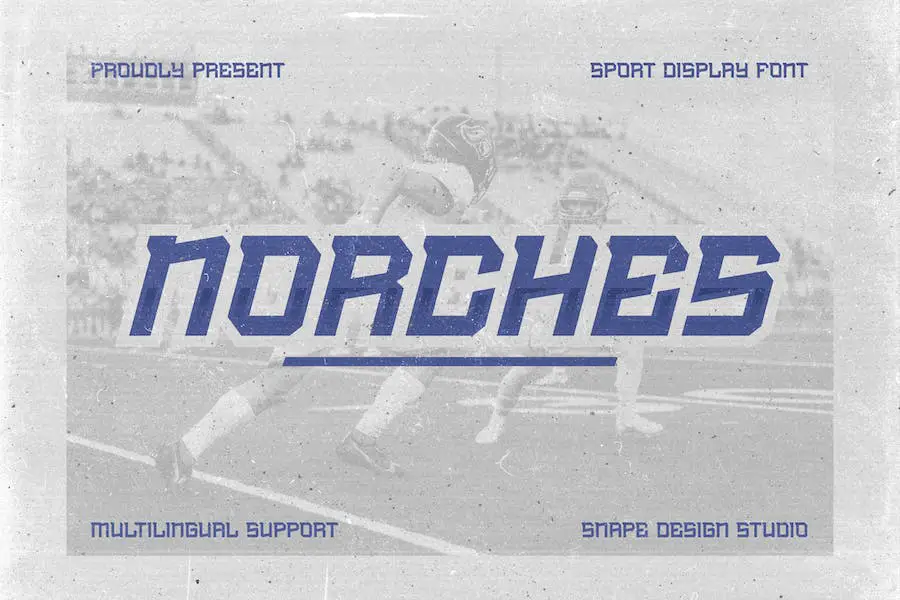
Norches este un font sport care captează atenția și sporește impactul oricărui proiect cu estetica sa îndrăzneață și puternică. Este alegerea perfectă pentru a adăuga o notă vibrantă modelelor inspirate de sport care trebuie să iasă în evidență.
Acest font de fotbal este conceput special pentru cei care doresc să-și facă proiectele izbitoare și de impact vizual. Simțul său îndrăzneț surprinde esența sportului și atrage atenția asupra elementelor cheie din design-ul tău.
Cu Norches, puteți crea fără efort un aspect puternic și dinamic pentru postere, bannere, logo-uri și multe altele.
Designul elegant și modern al fontului emană încredere și energie, perfect potrivit pentru proiectele legate de sport.
Indiferent dacă proiectați pentru o echipă profesionistă de fotbal sau creați grafică pentru un eveniment sportiv, Norches se va asigura că munca dvs. surprinde entuziasmul și spiritul jocului.
Radley
Radley este un font urban cu majuscule, conceput special pentru branding și logotip sportiv. Cu designul său îndrăzneț și izbitor, este alegerea perfectă pentru designerii grafici care doresc să-și îmbunătățească proiectele.
Acest font vine în patru stiluri diferite, fiecare dintre ele adaugă o notă unică lucrării tale. Fie că proiectați pentru o echipă de fotbal sau creați grafică cu tematică sportivă, Radley vă va face proiectul cu adevărat în evidență. Obțineți-l acum și duceți-vă design-urile la nivelul următor.
Cu Radley, puteți oferi proiectelor dvs. legate de sport un aspect profesional și șlefuit. Stilul său urban adaugă o atmosferă modernă și neclintită, făcându-l perfect pentru branding sportiv.
Fie că proiectați un logo pentru o echipă de fotbal sau creați materiale promoționale pentru un eveniment sportiv, Radley vă va ajuta să faceți o declarație îndrăzneață. Formatul său cu majuscule asigură că desenele dvs. au impact și sunt ușor de citit.